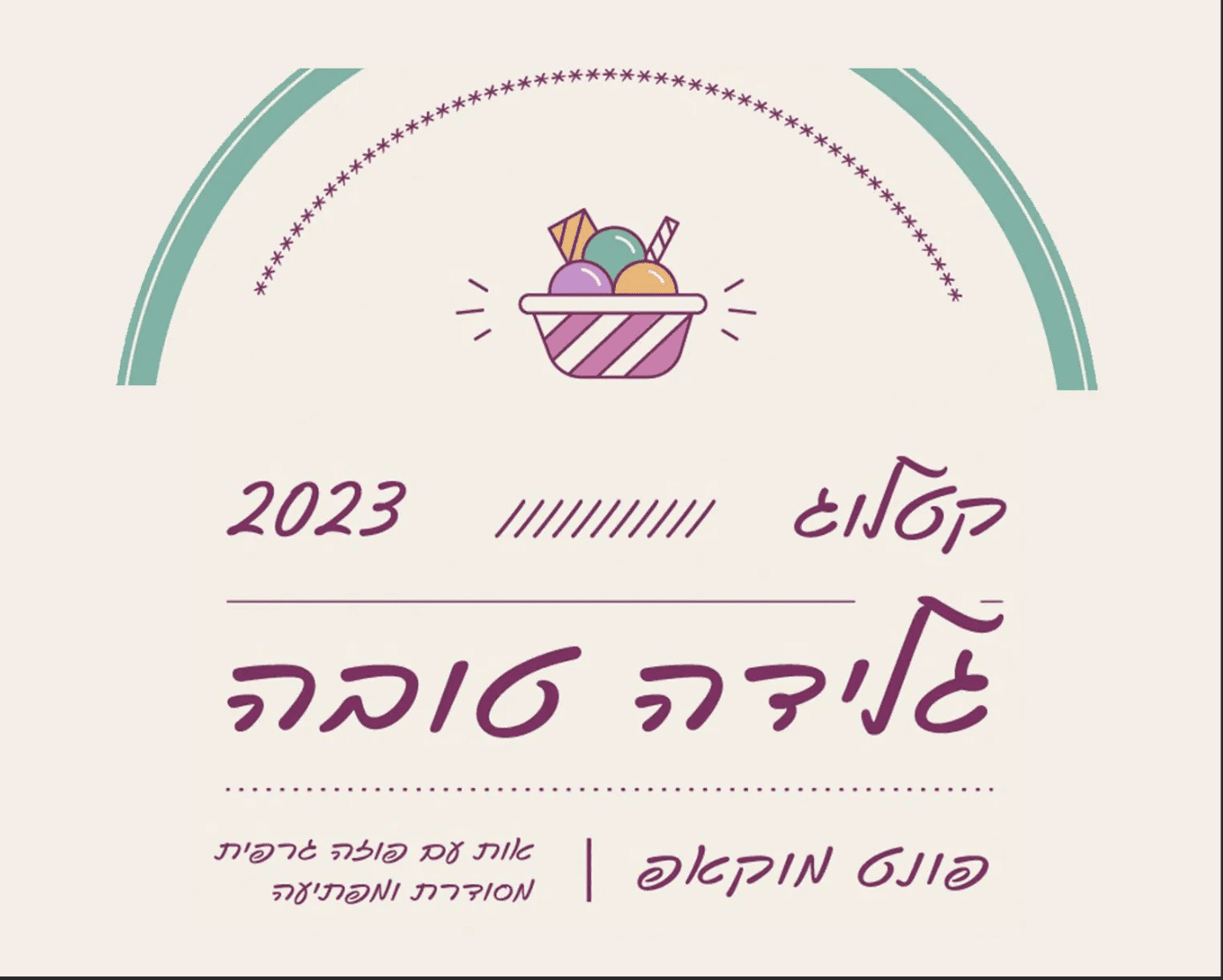
מוקאפ
מוקאפ / Fb Mockup
• שם הגופן:מוקאפ
• מעצב הגופן:נדב עזרא
• סגנון:רהוט
• תכונות: אוונגרדי אלגנטי אקזוטי הומניסטי חושני מעוגל מתוק נוסטלגי עדין קוסמטי
סיפור הגופן:
זהו גופן מוקאפ טיפוס אות רהוט הומניסטי חופשי עם פוזה גרפית מסודרת ומפתיעה בגבולות שנמתחים ממש עד הקצוות.